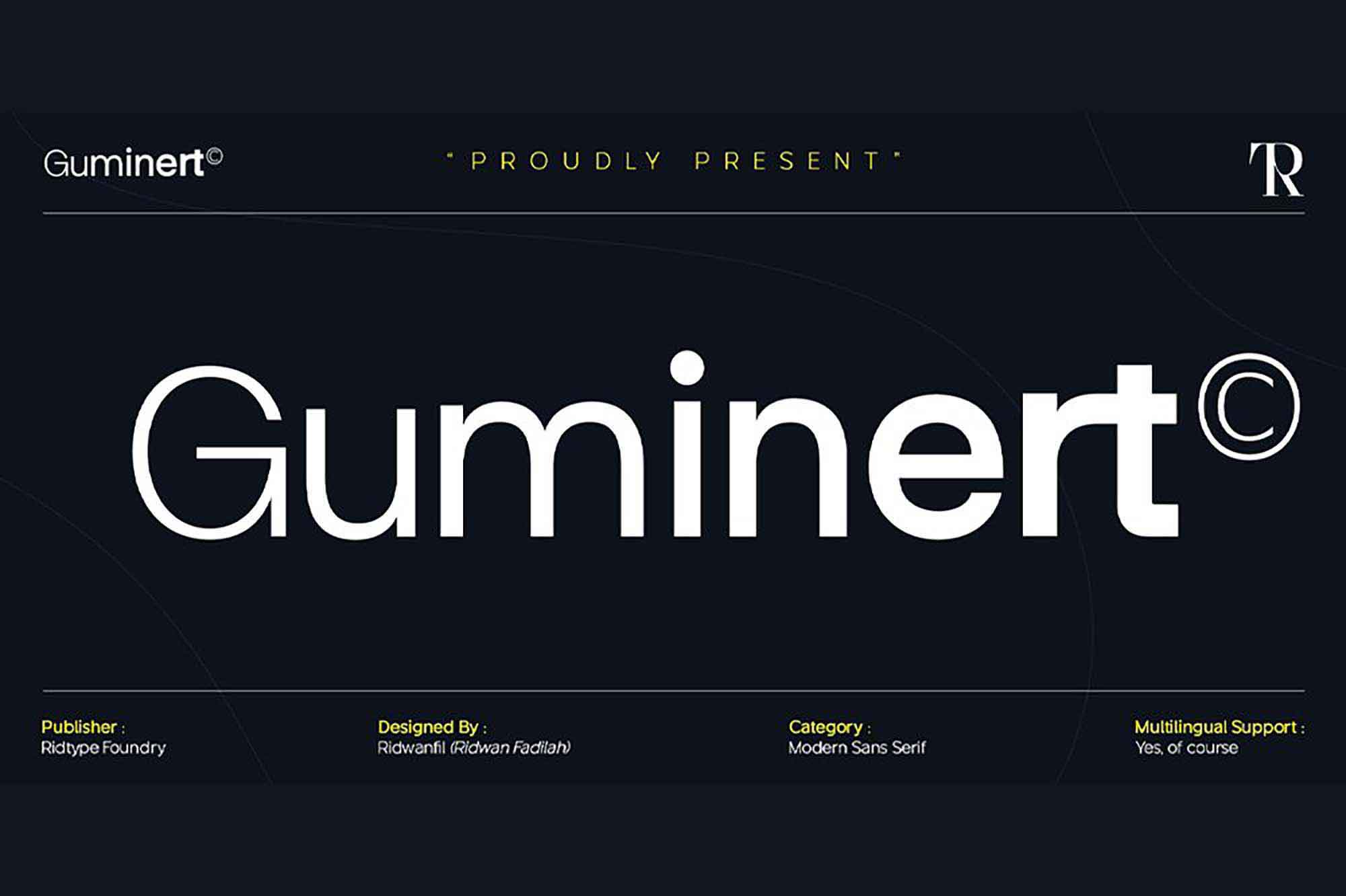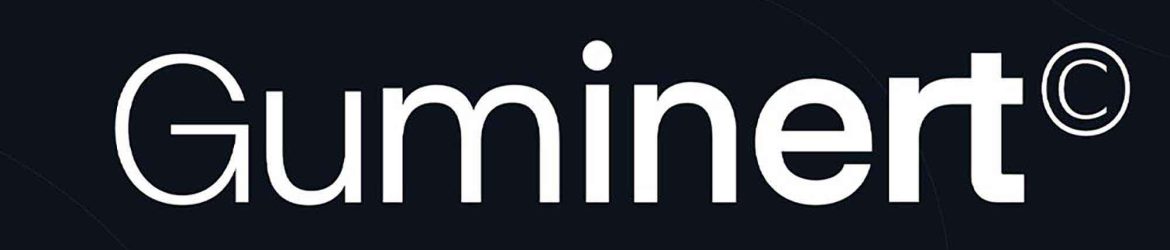
Ridwanfil desenvolveu a fonte Guminert Sans com um conceito moderno, simples e dinâmico. Esta fonte apresenta muitas alternativas, ligaturas entre letras maiúsculas e minúsculas, além de símbolos de caracteres de apoio. Com essa ampla gama de personalização, ela pode ser adaptada conforme as necessidades. Se você está procurando por uma fonte de estilo sério e contemporâneo, Guminert Sans pode ser perfeito para você. Suas linhas acentuadas e linhas levemente desenhadas proporcionam um design que não só é moderno, mas também permite uma flexibilidade de uso muito grande. E isso tudo dentro da categoria de Mockups, sem dúvida um recurso indispensável para designers.